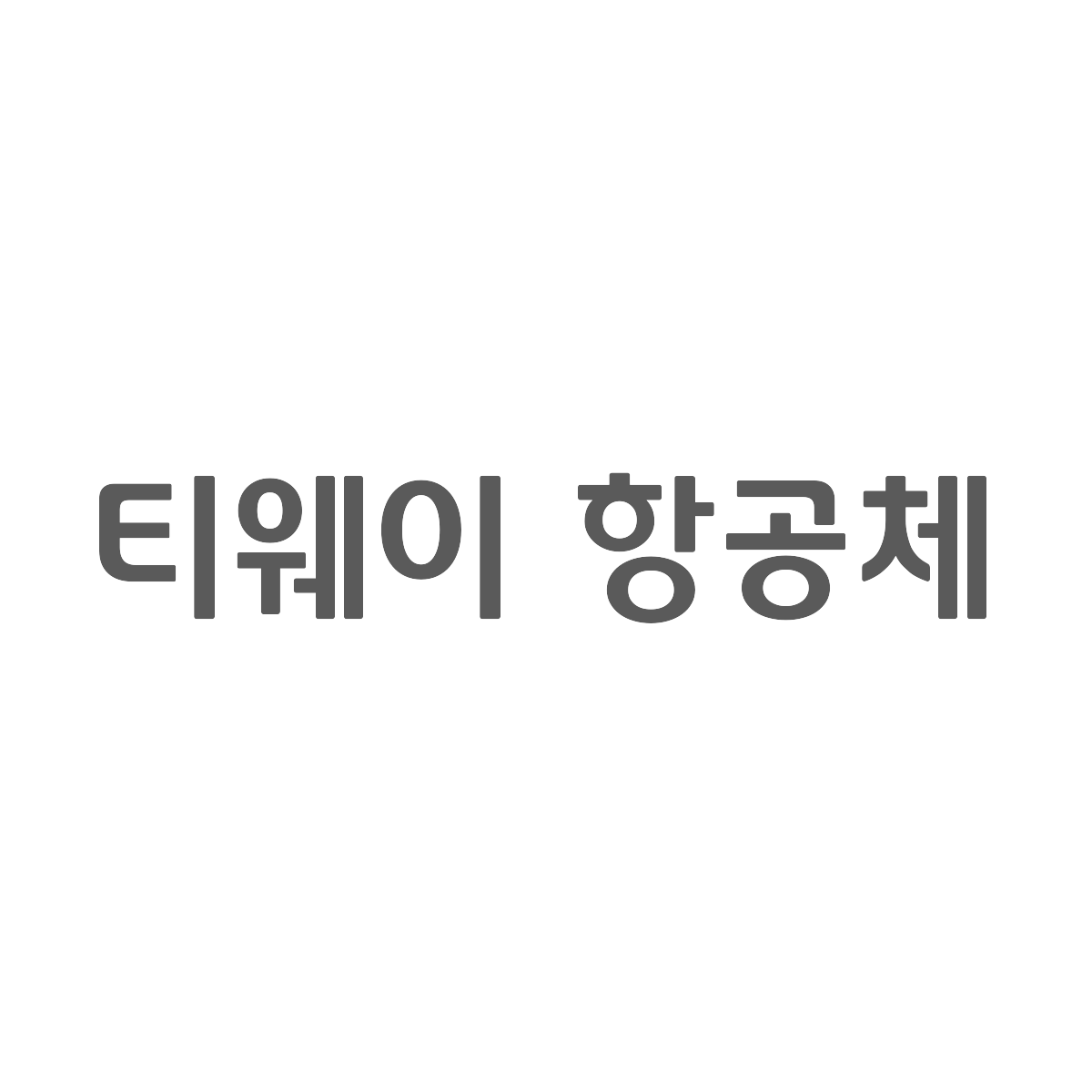
티웨이 항공체
제목용 서체에서 꽉 찬 Bold 서체로 파생된 디자인이며, 레트로적이지만 모던한 느낌을 살리기 위해 세리프를 너무 강하게 표현하지 않고 단순화했습니다. 새로 기둥의 시작은 붓 끝의 느낌을 살린 세리프, 맺음은 심플한 단면으로 자소 하나하나가 모두 개성이 강하다 보면 가독성은 물론 특징이 없는 서체가 되기 때문에 포인트가 되는 부분을 살리되, 그 특징을 돋보이게 하기 위해 다른 요소들은 심플한 단면으로 절제한 디자인입니다. 내리점은 티웨이항공의 아포스트로피('') + 비행기 터보팬을 회전시켜 자소를 디자인하였습니다.
• Sans,민부리